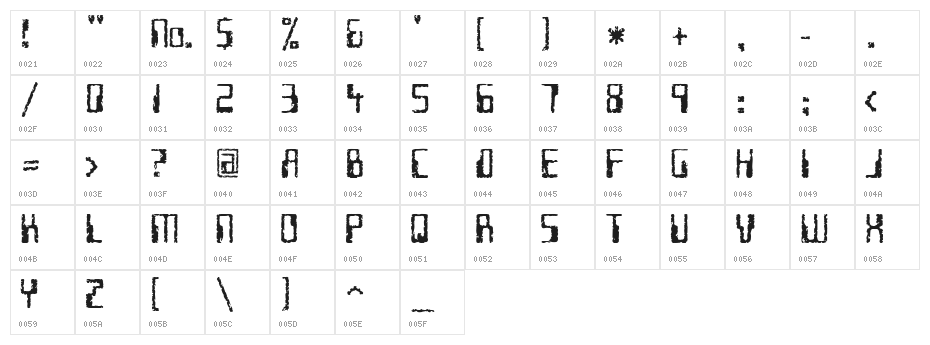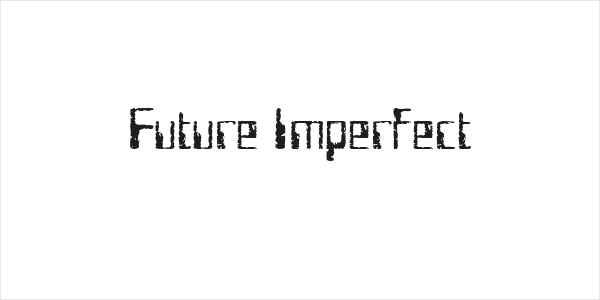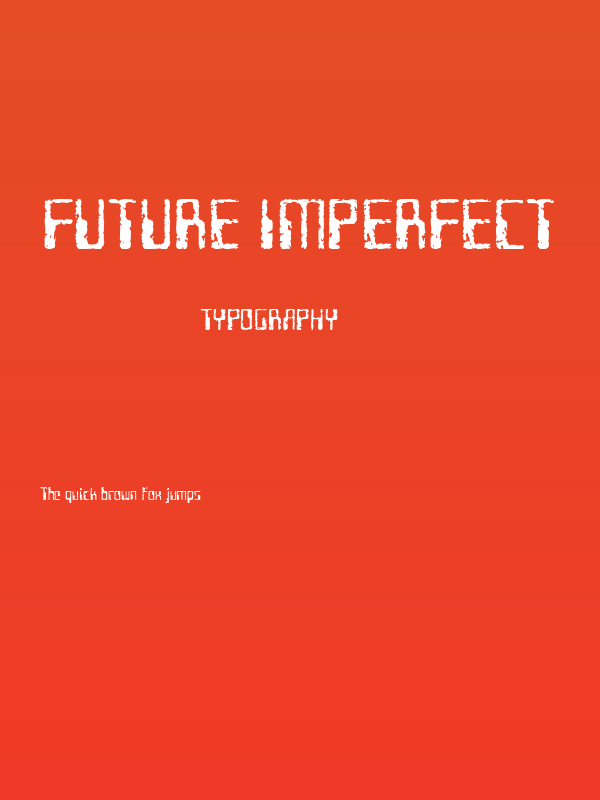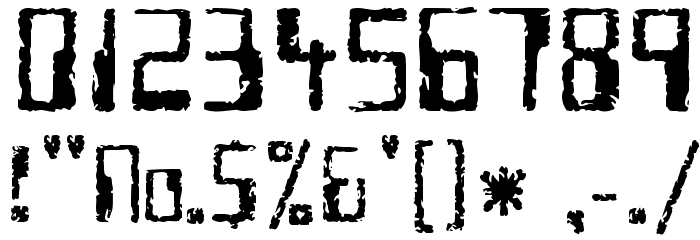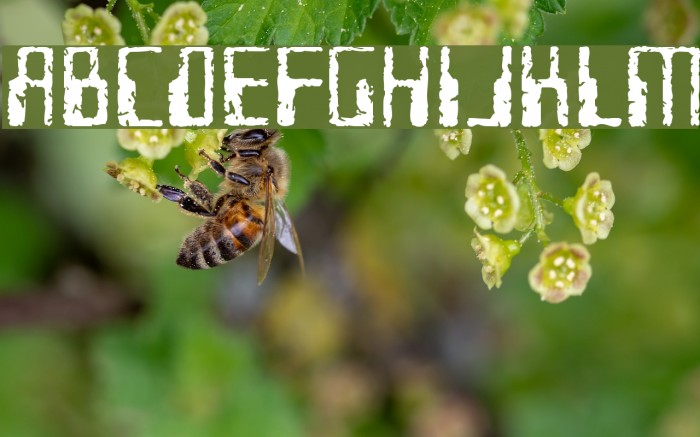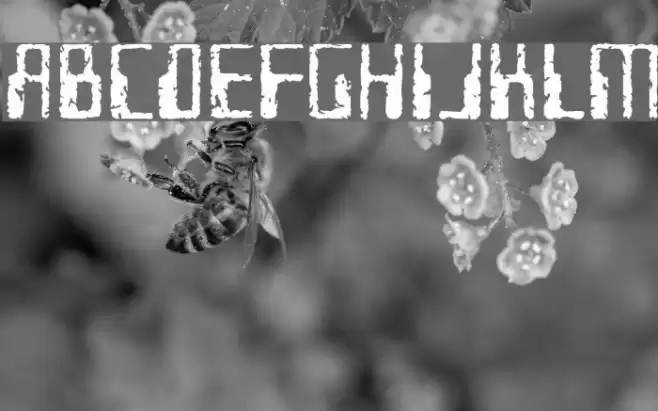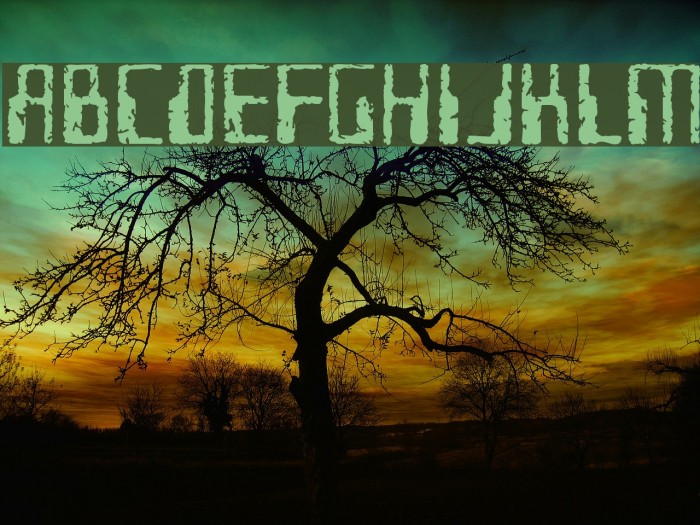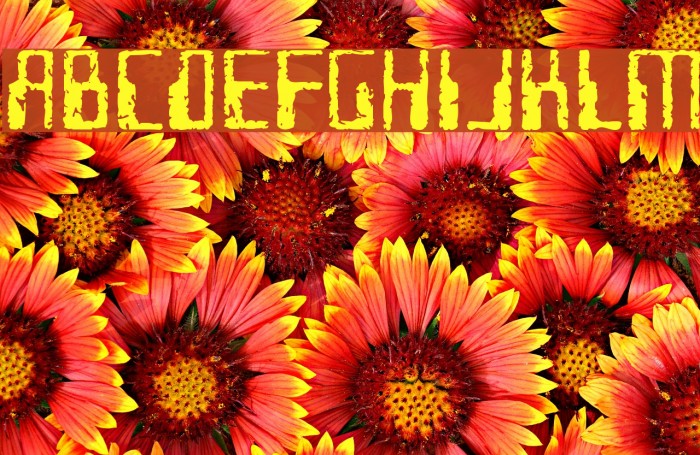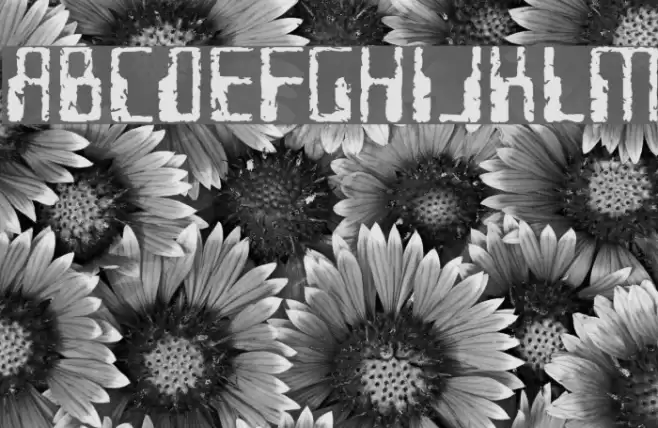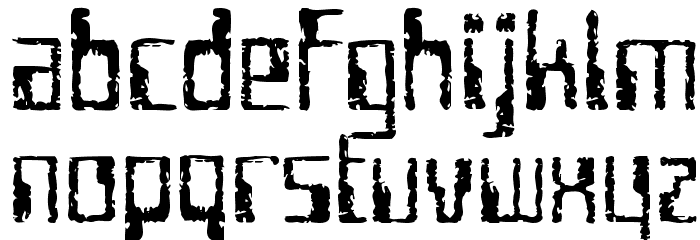
Future Imperfect Font
✎ Distorted Eroded
| Proyectos propuestos | Ideal for posters, album covers, video game graphics, or any project needing a gritty, industrial look. |